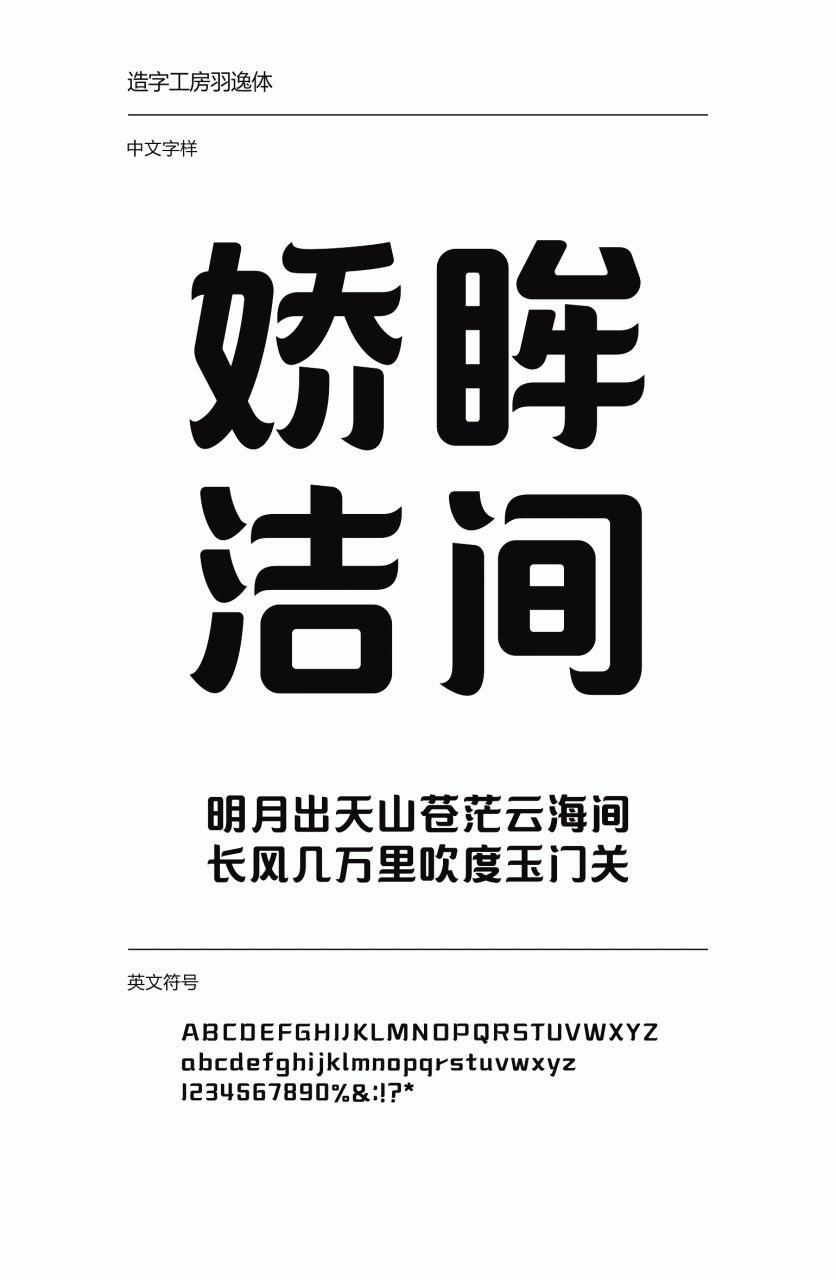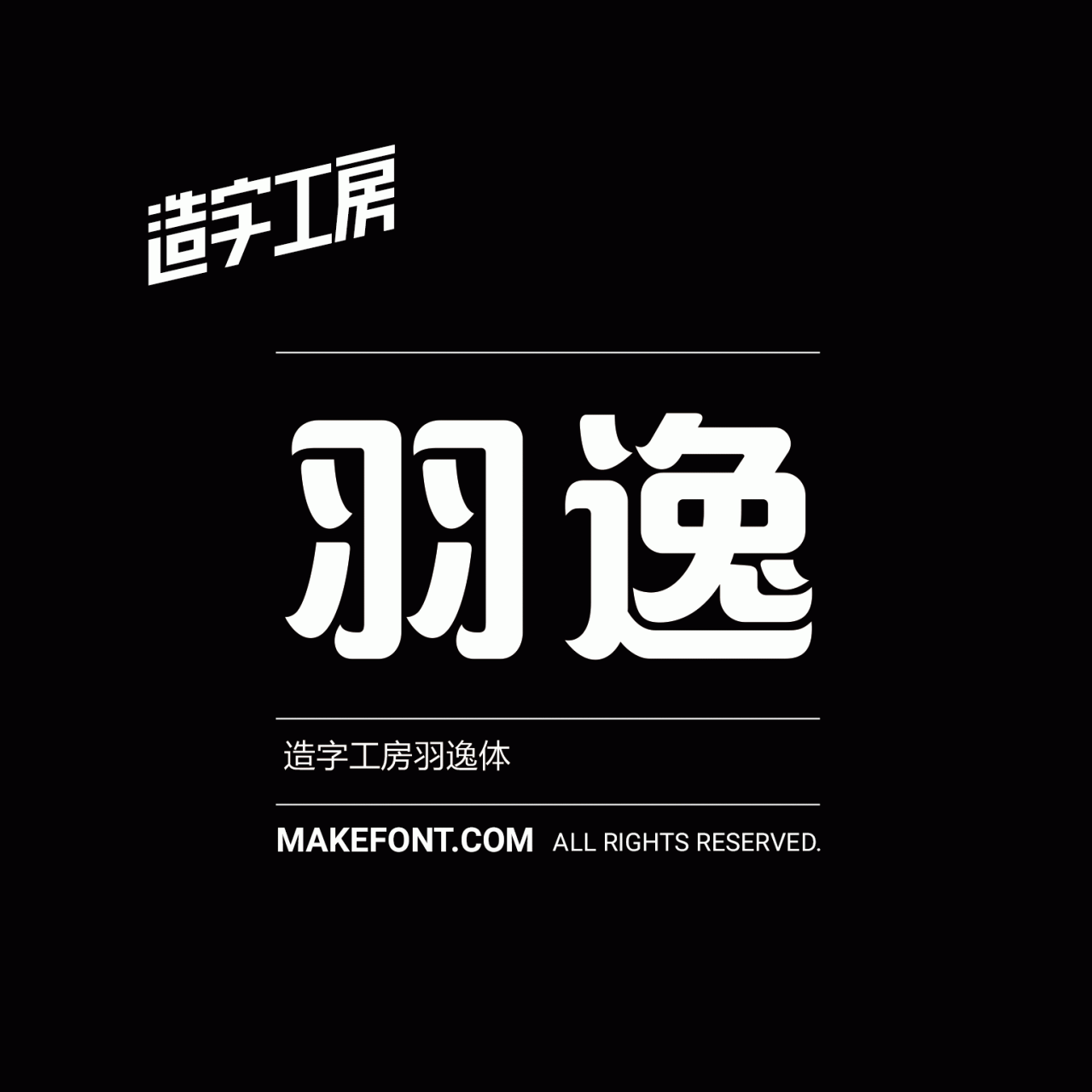
造字工房羽逸体,字形圆润舒展、端庄柔美,笔触舒展流畅,粗细均匀,转折处婉转有度,给人以精致、柔美之感,有极强的视觉表现力。适用于大标题及个性品牌设计推广等环境。本字体为简体字库,采用OpenType/CID格式,Adobe-GB1-5编码。基于中华人民共和国GB2312-80字符集标准,另按需添加101个汉字。共收容字数6864CJK汉字,ASCII常用字符100个。